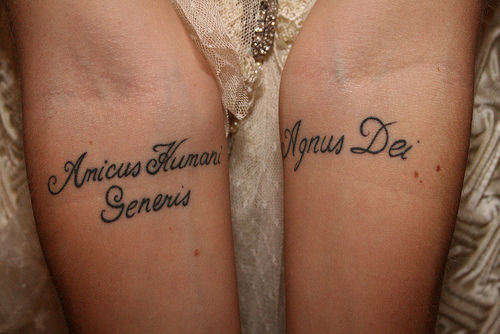
Hallo allerseits :D
Ich wollte fragen ob jemand weisst wie diese Schrift hier heisst,
ich finde sie wunderschön und würde mich auf eine antwort freuen :)
die Schrift sieht für mich nach Handarbeit auf der Basis einer stark modifizierten Pen Tweaks Three aus der SSI Collection aus. Legale Bezugsquellen oder Links die den Ansprüchen dieses Forum entsprechen kann ich nicht vorweisen. :?
Es heißt auch Amicus Humani Generis ... und nicht Amicus Kumani Generis! Auch hier hilft Google sicherlich unter dem Stichwort Tattooentfernung weiter. :|